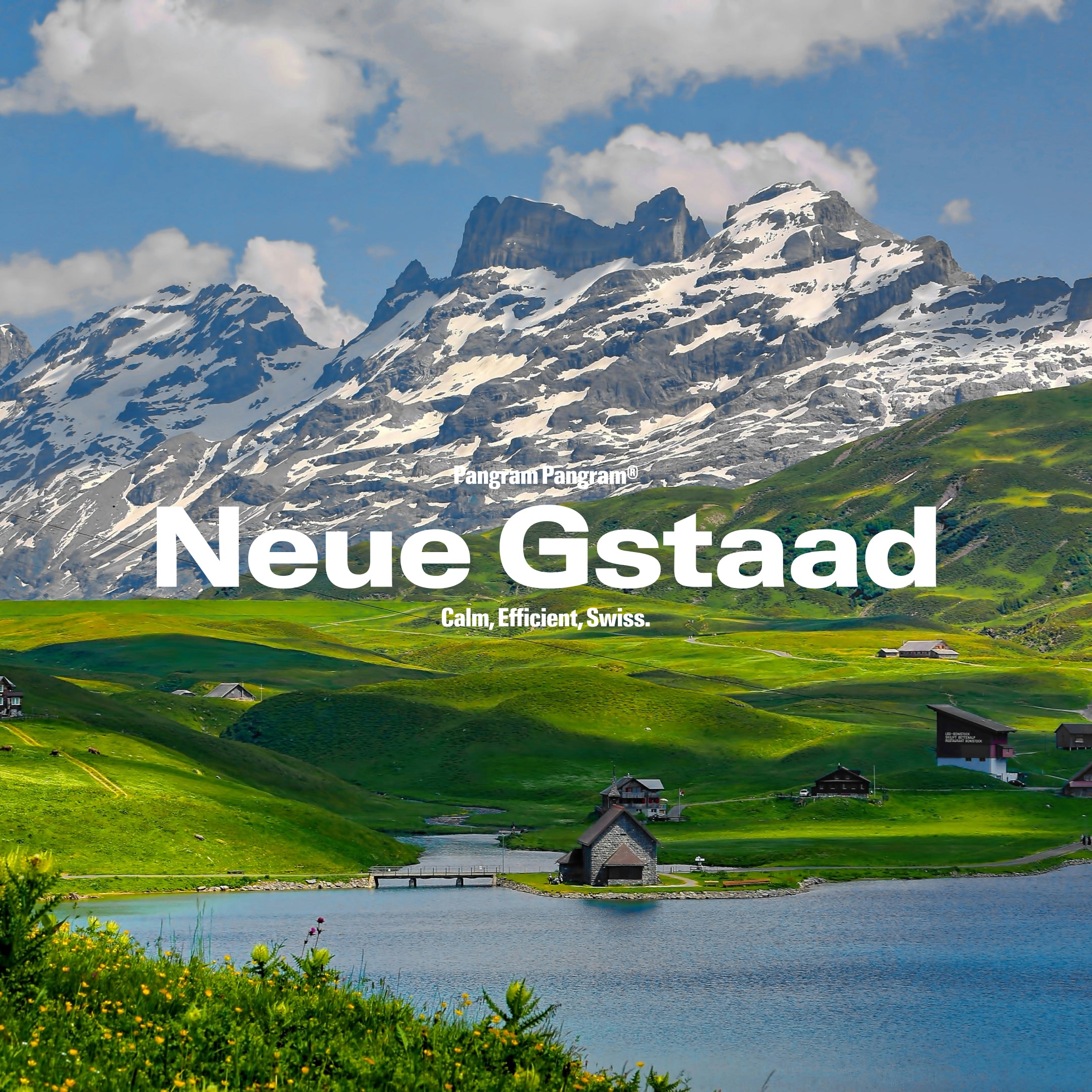
Neue Gstaad Wide
Le sens suisse du raffinement, du calme, de la confiance et de la précision.
Fonctionnalités de Neue Gstaad Wide
Calme. Efficace. Suisse.
Neue Gstaad est une famille de caractères contemporaine, façonnée par un sens nettement suisse du raffinement, du calme, de la confiance et de la précision. Conçue par Ian Party, elle dépasse les clichés régionaux pour embrasser une expression plus large et plus universelle du design suisse : une expression enracinée dans la clarté, la discrétion et une sophistication discrète. Lâchement inspirée par des géants typographiques, Neue Gstaad interprète ses références avec retenue. Sa structure se déploie à travers un système variable ultra-polyvalent, allant de Compressed à Expanded, permettant une gamme fluide de voix, des paramètres éditoriaux compacts aux compositions architecturales étendues.
Neue Gstaad évoque une sensibilité plutôt qu'un lieu. Elle suggère l'altitude sans excès, le luxe sans bruit, un équilibre cultivé entre tradition et modernité, discipline et ouverture. La famille comprend 112 styles, 7 sous-familles, et est conçue comme un système typographique complet et tourné vers l'avenir. Elle est riche en fonctionnalités OpenType et prend en charge un large éventail de langues basées sur le latin.
Enracinée dans l'héritage mais conçue pour l'avenir, Neue Gstaad reflète l'exploration continue de Ian Party de la typographie en tant que système vivant. C'est un design riche et complexe distillé dans une clarté essentielle, où la simplicité n'émerge pas de la réduction, mais de la maîtrise.
Nouvelle étape dans le développement d'un écosystème variable complet, Neue Gstaad incarne une idée singulière : une forme d'expression discrète, façonnée par la précision.